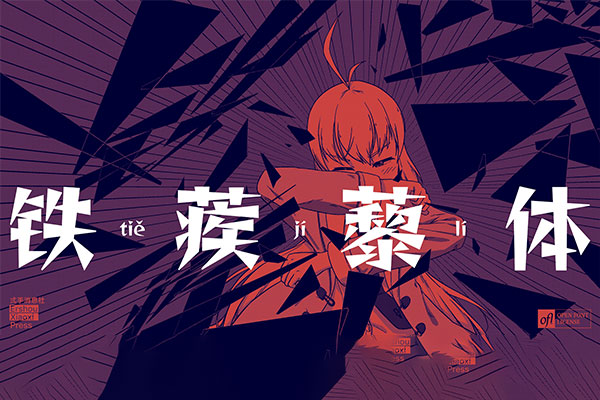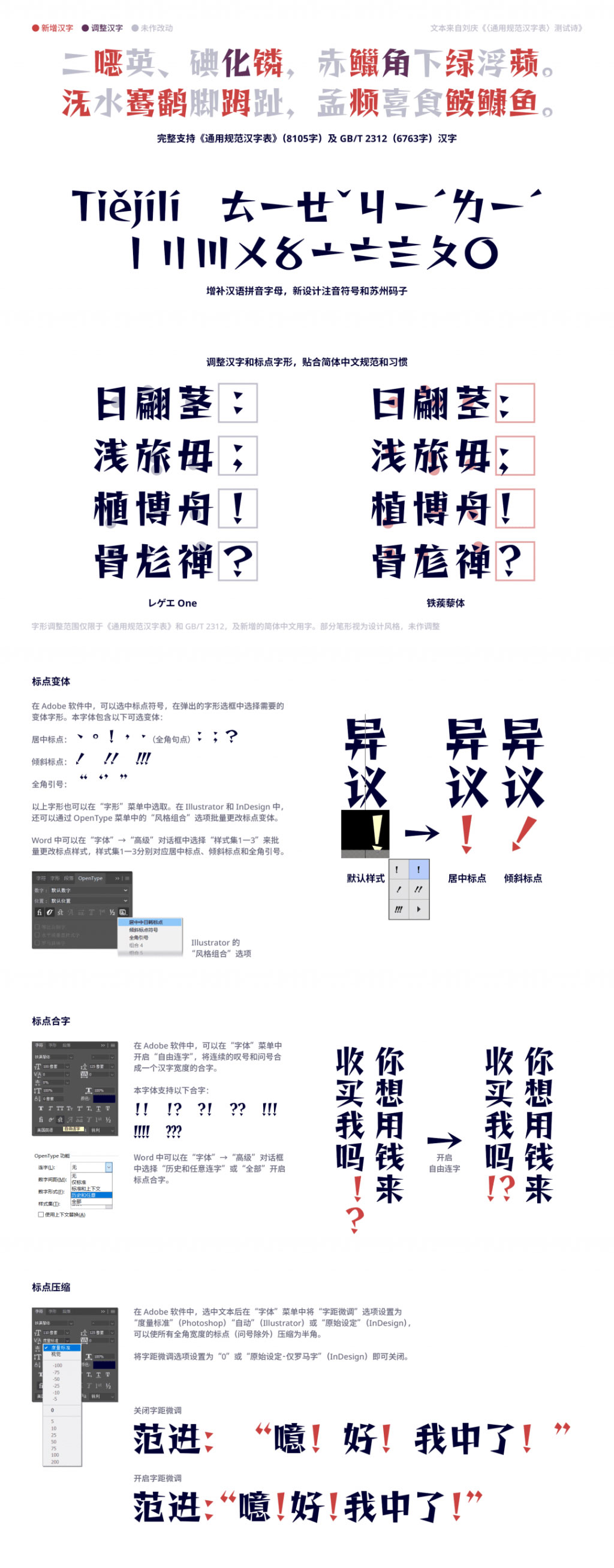
铁蒺藜体
铁蒺藜体(Tiejili)是由中国大陆的奈白不二(Naibunfu)日文字体レゲエ One进行扩展和调整字形,并添加了OpenType特性,以适应简体中文的使用需求。
铁蒺藜体的字形设计如其名字所示,呈现一种尖锐的艺术风格。在原版字体基础上,它完全支持《通用规范汉字表》(8105字)和GB/T 2312汉字(6763字),并适当增补了各专业领域的常用汉字,总计收录超过1万字,可基本满足简体中文的使用需求。
此外,铁蒺藜体还增补了汉语拼音字母,并重新设计了注音符号和苏州码子。
铁蒺藜体效果预览
铁蒺藜体字体效果预览